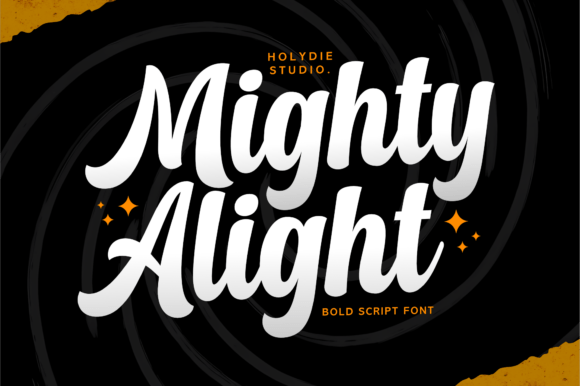
Mighty Alight
Mighty Alightのような高品質の素材をお探しの場合、このプレミアムパッケージはクリエイティブなプロジェクトに素晴らしい選択です。
POD(オンデマンド印刷)製品、結婚式の招待状、またはソーシャルメディアのグラフィックを作成している場合でも、Mighty Alightは理想的です。